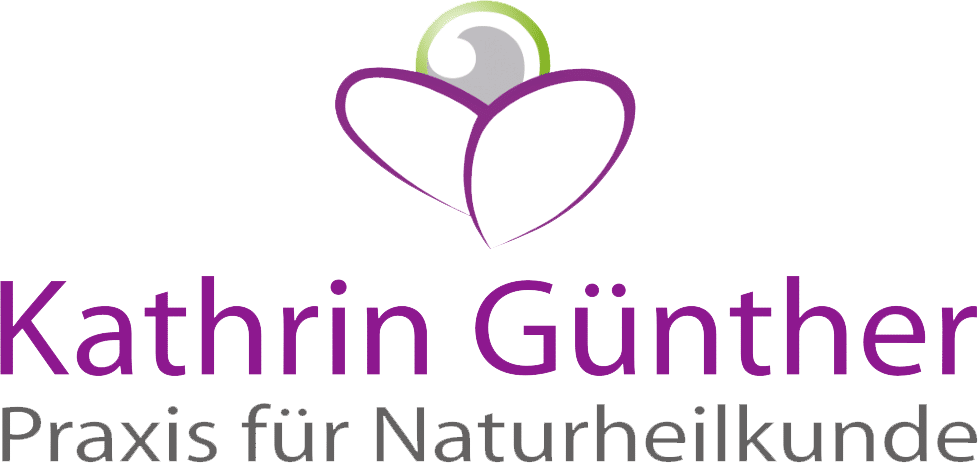
Welche Schrift ist das? (Naturheilkunde)
"Natürlich …" ist aus der "Gunny", ebenfalls vertikal gestaucht.
Schon wieder war der  Bertel schneller ... :cry:Während ich noch nach einem Link für die Schrift suche ...
Schon wieder war der  Bertel schneller ... :cry:
Ich hab doch schon immer gesagt, er hat eine echte Merlin3000 Kristallkugel mit Typografieerweiterung.